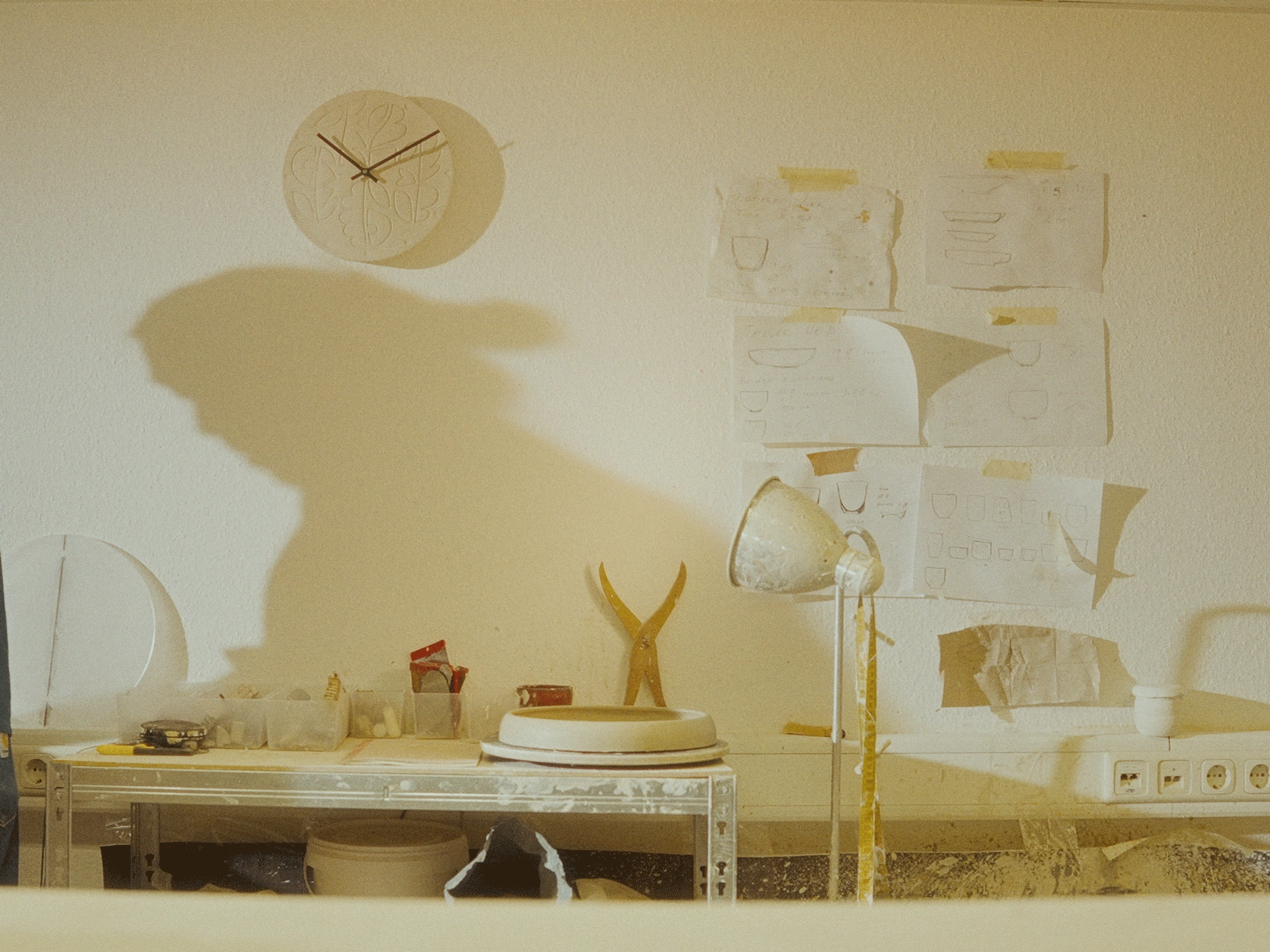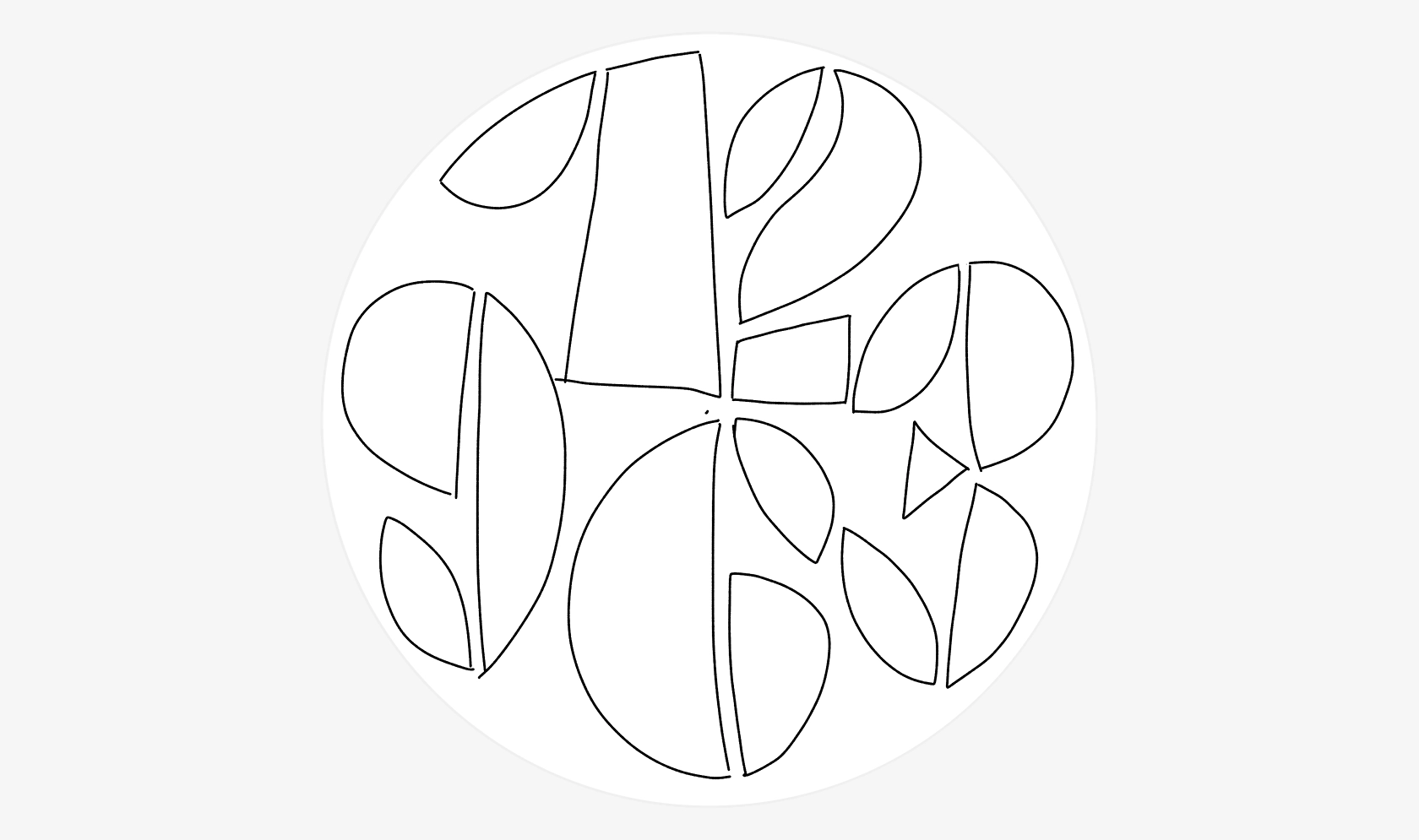
Цветы и время: Type O’Clock X Contrast Foundry
Как для вас выглядит отсчёт времени? Если бы мы попросили вас закрыть глаза и его представить, что бы вы увидели? Электронный будильник со светящимися футуристическими цифрами? Или кухонные часы со строгими стрелками, мерно переходящими от одной точёной цифры к другой? Лучик солнца, пробравшийся в дом и скользящий по обоям, меняя цвет с золотого на красный?
Нас в CoFo очаровало время в тот момент, когда мы познакомились со студией Type O’Clock. Основанная дизайнерами Джиму Кобаяши и Лукасом Шульцем, она раскрывает его через керамические циферблаты уникальных часов. В своей мастерской в Дюссельдорфе, Джиму и Лукас научились заключать время в хитрые переплетения механизмов и цифр, размещенных в рукотворной керамике. Все часы подвергаются обжигу в печах, нагревающихся до 1000 градусов по Цельсию, после чего в каждый механизм помещается точный немецкий кварцевый хронограф.
Ещё один ключевой элемент часов Type O’Clock скрывается в волшебстве цифр. Помните, мы спрашивали, каким вы видите время? В студии CoFo время раскрылось цветами, соединяющими камень и время, напоминающими нам о целебных свойствах природы, стоящей над любыми испытаниями. Оно помогло нам создать новое, уникальное видение часов, временно объединившее наши студии для этой коллаборации.
Мы экспериментировали с формой и контрформой шрифта, создавая цифры. Контур цифр рельефный, а контрформы, лежащие на поверхности, становятся главным и самым важным элементом дизайна. Наши цифры живые, они цветут и распускаются на тёплой керамике циферблата. Часы являются элементом, подобным земле, песку и камню, недвижимым и спокойным. И как положено земле, они поддерживают жизнь и время цветов, заполнивших их шероховатую поверхность.
Первый эскиз Егора Головырина